はじめまして。自分の名前くらい綺麗にかけたらなぁと、練習しているのですが、明日香がうまく書けません。 いろいろ参考にし、明は月の一画目が中心だということは意識して書くのですが、そうすると明だけ左にズレているように感じるのです。 コツはありますでしょうか?
練習方法や、文字の見方の参考になれば嬉しいです(^o^)!
まず、いつも通り(LINE@のお友達にはおなじみのマス目)書いてみました。
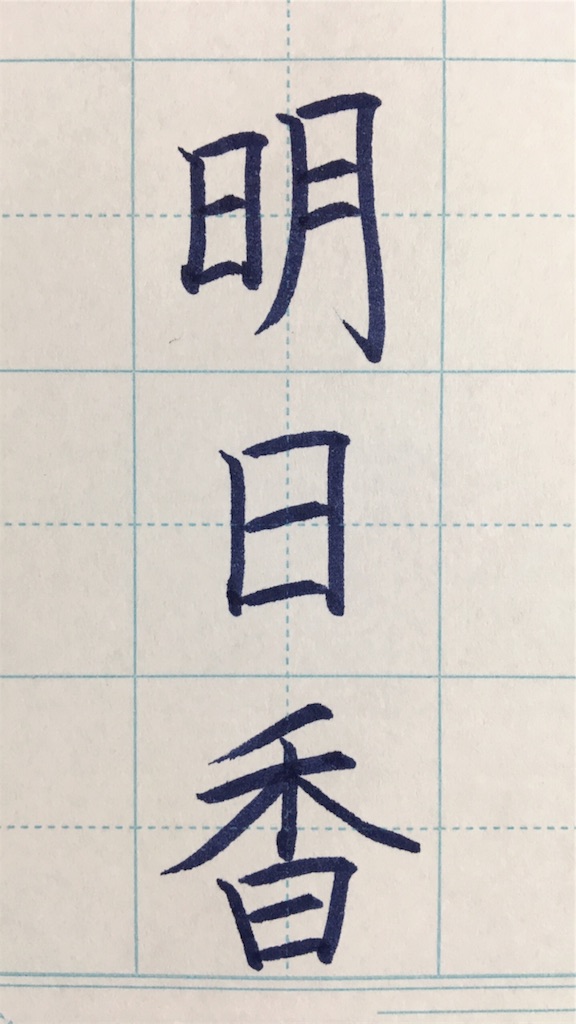
こんな感じ。まっすぐ書けてる、と思います。
さて、ここで注目するのは、マス目=書くスペースに対して、文字がどのように収まっているか。
今回は、質問が「明」が左にズレているように感じる、ということでしたので、左右の余白がどのくらいなのかを示してあります。
中心線の意識ももちろん大切ですが、私はいつも、「周りの余白がどうなっているか」を見るようにしています。
「明」という字の左右の余白、ほぼ同じくらいになっています。
「日」は少し小さめに書きます。こちらも左右の余白は同じです。
「香」は左右払いがありますので、左右均等にしっかり広げます。
こんな感じで、色んな「余白」に注目してみると、書くスペースに対して文字をどのように収めるか、が分かってくると思います。
面倒くさい…かもしれませんが、「きれいな文字」を書くには欠かせない要素です。
さて、マス目で大体のバランスが掴めたら、白紙で練習してみましょう。
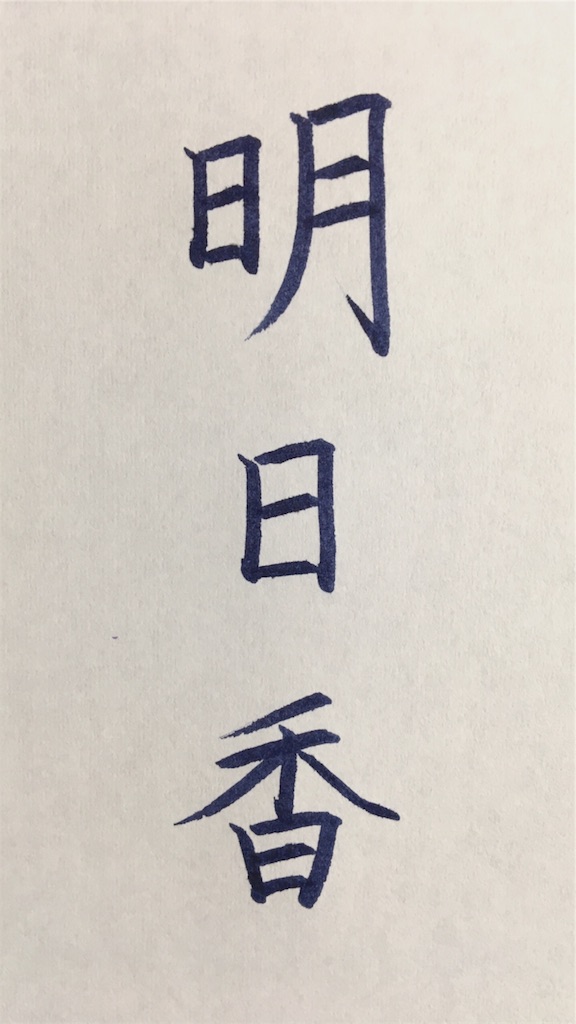
こんな感じ。
マス目で書いた余白のポイントと、ほぼ同じように書けていると思いますヽ(・∀・)
このように「余白」にも注目する事で、文字の中心・中央に収める書き方が分かり、結果的にがまっすぐ書けるようになってきます。
★「明」の日と月の幅についても質問をいただきました。月の方が少し広めになっていると思います。